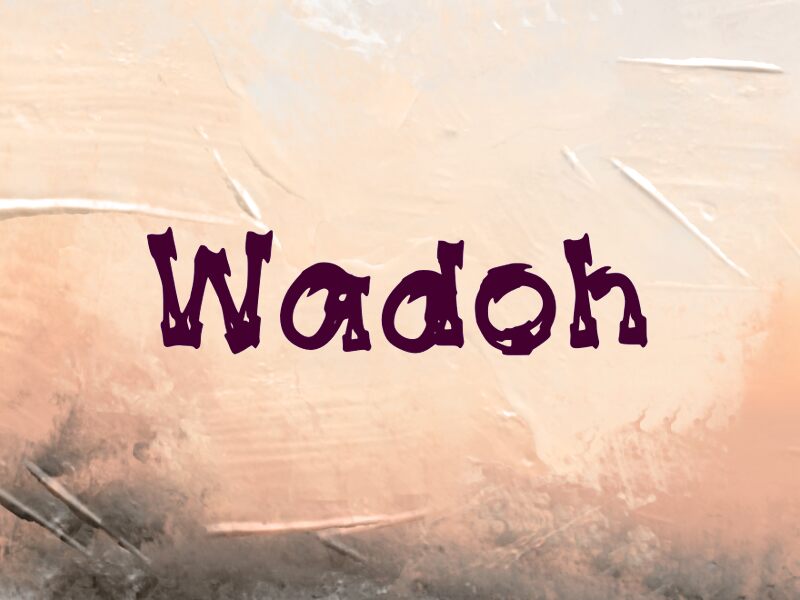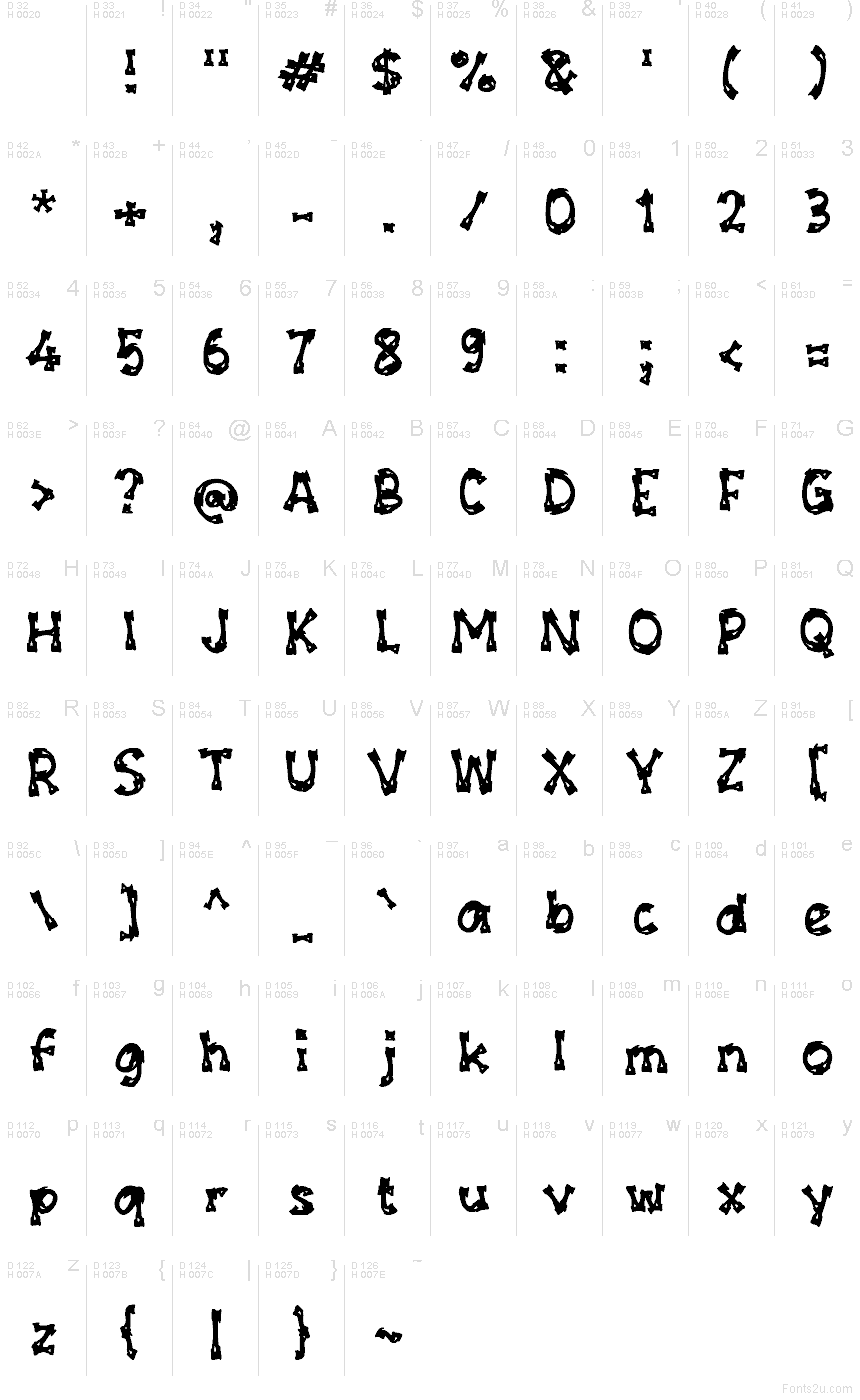
Wadoh de Wep est une police d'affichage gratuite au style folk-art, dotée d'un esprit brut et artisanal. Les lettres semblent sculptées et légèrement indisciplinées, avec leurs courbes épaisses, leurs jonctions serrées et leurs petites pointes en forme de cornes qui donnent à l'ensemble une esthétique brute, presque digne d'une gravure sur bois.
C’est le choix idéal pour des titres d'affiches, des pochettes d'albums, du packaging indépendant, l'identité visuelle de cafés ou des flyers d'événements où l'aspect fait-main prime sur la finition lisse. En tant que police gratuite, Wadoh est également très efficace pour les titres et les textes courts, car ses silhouettes découpées et ses formes dynamiques insufflent de la vie au moindre mot.
Wadoh
Présentation et spécimen de la police Wadoh